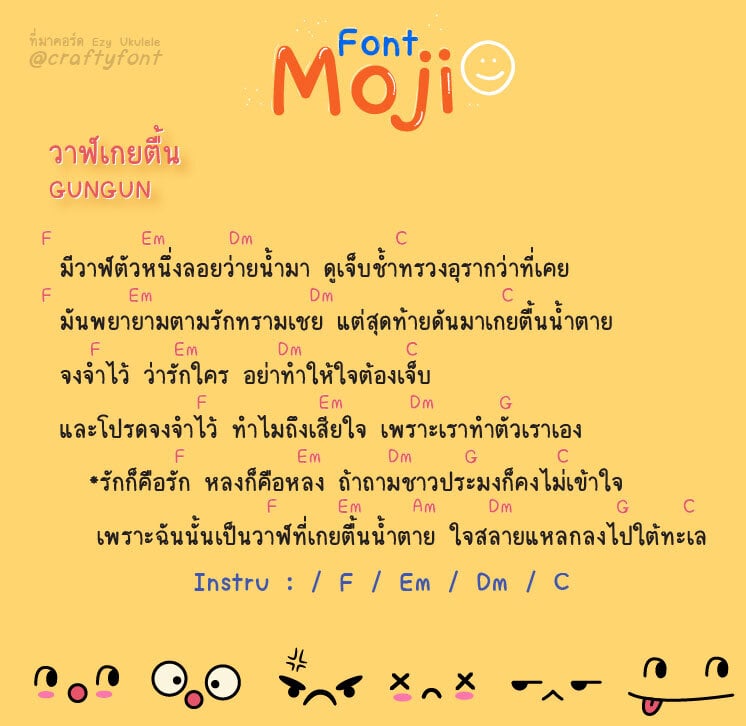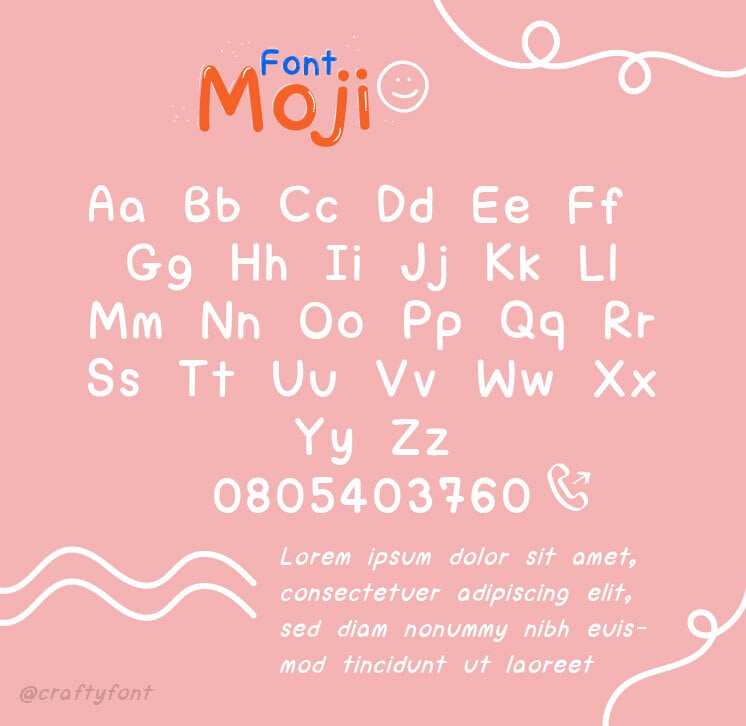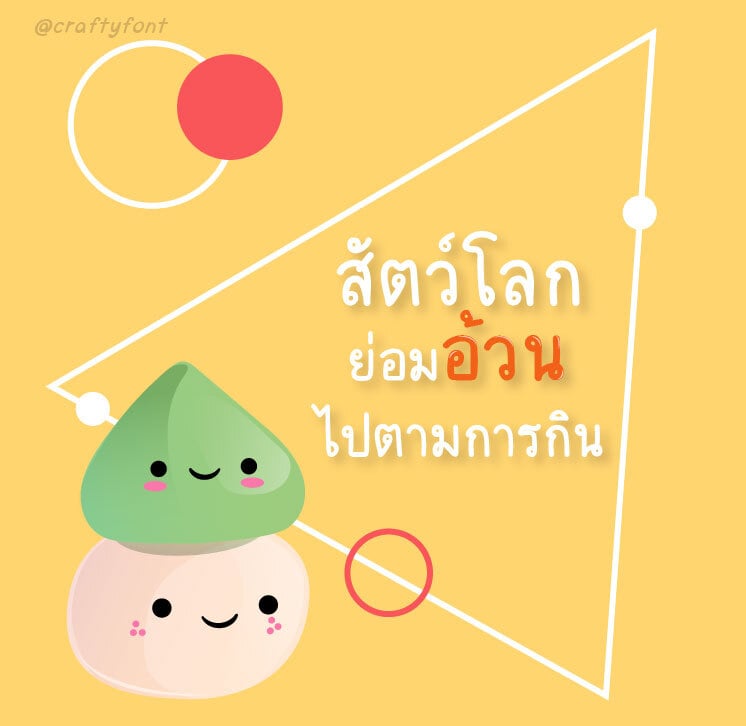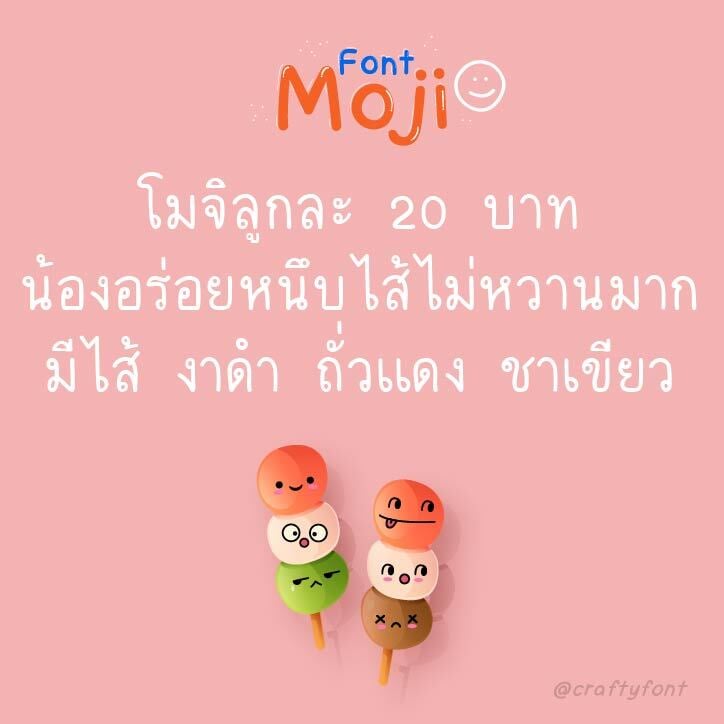
Moji Font (ฟอนต์โมจิ)
ฟอนต์โมจิ พัฒนาต่อมาจากฟอนต์เบนจามินเมื่อปีก่อน ทำมาเรียบเรียงใหม่ ให้น้องละมุนและอ่านง่ายมากยิ่งขึ้น หวังว่าทุกคนจะชอบนะคะ 🥰
ฟอนต์โมจิมีทั้งภาษาไทยและภาษาอังกฤษเลยนะคะ แฟมิลี่เซ็ตนี้มี 6 ขนาดด้วยกัน ทั้งตัวหนา ตัวปกติ ตัวบาง และตัวเอียงสำหรับทุกน้ำหนัก สัญลักษณ์บวกลบคูณหารมีให้ใช้ครบ ฝากไว้ในอ้อมอกอ้อมใจพี่จ๋าด้วยนะจ๊ะ 🙏🏻